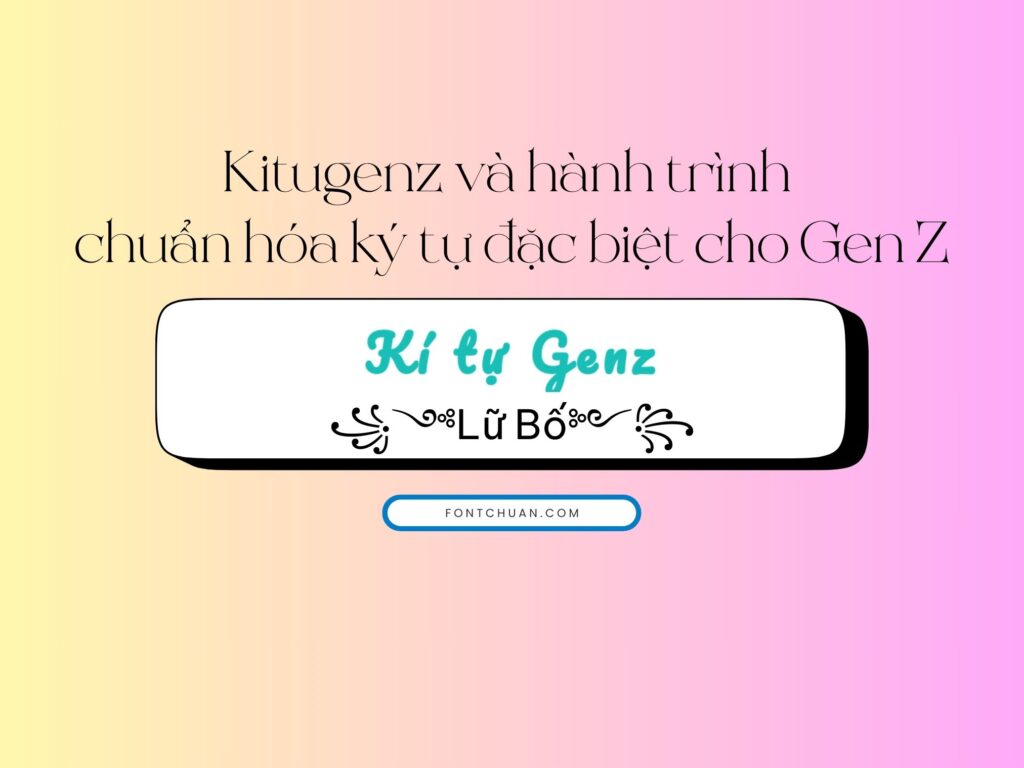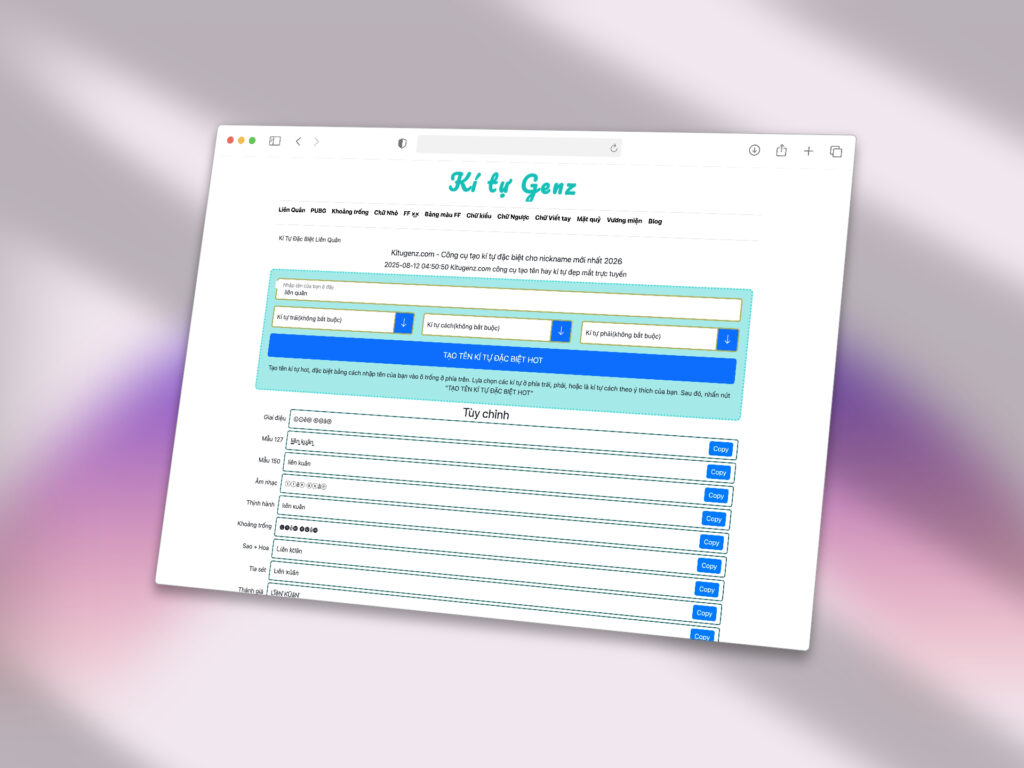
Kitugenz và hành trình chuẩn hóa ký tự đặc biệt cho Gen Z
Gen Z thích chữ kiểu. Tên game, bio TikTok, caption Instagram đều cần khác biệt nhưng vẫn dễ đọc. Kitugenz.com đáp ứng nhu cầu ấy bằng công cụ tạo ký tự đặc biệt và chữ kiểu. Khi người dùng tăng nhanh, một vấn đề xuất hiện: cùng một chuỗi ký tự nhưng hiển thị không đồng nhất giữa iOS, Android, web và các sảnh chờ trò chơi. Có nơi hiện ô vuông. Có nơi lệch dòng. Có nơi vỡ emoji. Kitugenz quyết định sử dụng dịch vụ chuẩn hóa ký tự của Font Chuẩn để xử lý tận gốc.
Bối cảnh và bài toán
Người dùng đến Kitugenz để đổi chữ rồi sao chép đi khắp nơi. Chuỗi tạo ra phải ổn định khi đổi nền tảng, đổi trình duyệt, đổi font. Thực tế có nhiều glyph trông giống nhau nhưng thuộc code point khác nhau. Một số nằm trong vùng Compatibility. Một số ở dạng Fullwidth. Một số lại phụ thuộc hệ thống fallback font của thiết bị. Khi thiếu chuẩn, nội dung có thể rụng dấu, dính khoảng trắng lạ, mất căn dòng. Trải nghiệm giảm. Khả năng tìm kiếm cũng bị ảnh hưởng khi bot đọc phải ký tự không tiêu chuẩn.
Mục tiêu
Mục tiêu đầu tiên là giữ chất Gen Z gồm ngầu, cute, tối giản, glitch nhưng vẫn đọc được ở mọi nơi. Mục tiêu tiếp theo là nâng tỉ lệ hiển thị đúng trên TikTok, Instagram, Facebook, YouTube, Discord và các trò chơi như Free Fire hay Liên Quân. Ngoài ra cần giảm lỗi sao chép dán và giảm thời gian tạo tên. Cuối cùng là giữ khả dụng cho máy tìm kiếm. Mỗi chuỗi nên có phiên bản Unicode thuần để lập chỉ mục ổn định.
Quy trình chuẩn hóa bốn pha
Pha một là kiểm thử và đo lường đa nền tảng. Font Chuẩn dựng ma trận thử nghiệm gồm iOS, Android, Windows và macOS. Trình duyệt gồm Chrome, Safari và Edge. Môi trường trong game cũng được đưa vào kịch bản. Hệ thống ghi nhật ký lỗi theo chuỗi và theo nền tảng. Các chuỗi được đối chiếu theo code point. Quy tắc phát hiện confusable giúp phân biệt chữ A Latin và А Cyrillic. Kết quả chỉ ra nhóm rủi ro tập trung ở NFKC Compatibility, Fullwidth Forms và một số ký tự tổ hợp.
Pha hai là xây dựng Bảng Ký Tự An Toàn Gen Z. Nhóm dự án lập danh sách ký tự an toàn theo nền tảng. Mỗi ký tự rủi ro có quy tắc thay thế tương ứng. Về chuẩn hóa, hệ thống lưu trữ theo Unicode NFC để thống nhất chuỗi. Khi xuất, hệ thống áp NFKC có kiểm soát để thu gọn biến thể mà vẫn giữ phong cách. Các chuỗi tổ hợp được giới hạn để tránh vỡ dòng. Với emoji, hệ thống định nghĩa fallback khi thiếu font emoji bản địa.
Pha ba là thiết kế hệ chữ và hướng dẫn sử dụng. Kitugenz có nhiều preset. Nhóm tái cấu trúc thành các bộ theo ý định tìm kiếm và ngữ cảnh dùng. Nhóm Cute dùng cho bio và caption. Nhóm Ngầu và Glitch dùng cho tên game và clan. Nhóm Minimal dành cho hồ sơ nghiêm túc. Mỗi preset có tên chuẩn SEO, mô tả ngắn, nhãn rủi ro hiển thị và gợi ý ghép với font Việt hóa. Đề xuất sử dụng OTF đậm cho tiêu đề và WOFF2 gọn nhẹ cho nội dung dài. Hướng dẫn quy định kerning, tracking và line height để chống đứt dòng. Cấu hình fallback font theo từng hệ điều hành giúp giảm lệch kiểu.
Pha bốn là triển khai kỹ thuật và trải nghiệm. Hai chức năng then chốt gồm bộ lọc ký tự và sao chép thông minh. Bộ lọc so chuỗi với danh sách an toàn. Nếu gặp rủi ro, hệ thống gợi ý thay thế tức thì và ghi lý do ngắn gọn. Sao chép thông minh cung cấp hai nút. Nút Giữ phong cách sao chép đúng kiểu chữ. Nút Plain Unicode tạo bản sạch để dùng cho SEO và những nơi chặn ký tự. Giao diện có xem trước theo nền tảng. Nhãn rủi ro hiển thị được đặt gần nút sao chép. Microcopy giải thích rõ: chuỗi này có thể không hiển thị trong một số trò chơi cũ. Phần nội dung chữ kiểu được cache và phân phối qua CDN để giảm độ trễ.
Quy trình chuẩn hóa bốn pha kitugenz
Kết quả và tác động
Sau khi chuẩn hóa, trải nghiệm hiển thị trở nên đồng nhất hơn. Người dùng truy cập kitugenz.com/ki-tu-dac-biet-lien-quan ít gặp ô vuông, đứt dòng và lỗi dán. Thời gian hoàn tất tên game giảm đáng kể. Tỷ lệ chia sẻ preset tăng vì người dùng tự tin rằng chữ sẽ hiển thị đúng ở nơi khác. Hình ảnh thương hiệu tốt hơn. Các màn hình chính giữ nhịp điệu thị giác ổn định về cỡ chữ, khoảng cách và độ đậm. Chuỗi văn bản trông mạch lạc dù người dùng đổi nhiều preset khác nhau.
Hiệu quả tìm kiếm cũng cải thiện. Mỗi trang preset có mô tả ngữ nghĩa rõ ràng. Từ khóa liên quan gồm chữ kiểu Gen Z, ký tự đặc biệt, đổi tên game và Unicode an toàn. Dữ liệu có cấu trúc phù hợp giúp máy hiểu nội dung. Phiên bản plain text dành cho bot hạn chế rủi ro đồng bộ. Điều này giúp công cụ tìm kiếm lập chỉ mục ổn định và tăng cơ hội hiển thị trích đoạn đẹp.
Bài học rút ra
Bài học đầu tiên là đẹp phải đi cùng chạy được. Unicode không chỉ là bảng mã mà còn là thỏa thuận giữa sản phẩm và hệ sinh thái. Tôn trọng NFC và NFKC giúp chuỗi bền vững khi truyền qua nhiều lớp. Bài học thứ hai là xem fallback font như dây an toàn. Cần định nghĩa stack rõ ràng và thử nghiệm theo kịch bản. Bài học thứ ba là không lạm dụng glyph hiếm ở vị trí trọng yếu như tiêu đề dài và khẩu hiệu. Hãy coi chúng là gia vị. Bài học thứ tư là quản trị bằng dữ liệu. Ghi lỗi theo code point, cập nhật danh sách an toàn theo quý và công bố thay đổi để cộng đồng nắm được. Bài học cuối là đặt tên preset theo ngữ nghĩa và mục đích. Tên rõ ràng giúp người dùng tìm đúng, máy hiểu đúng và mô hình ngôn ngữ trích xuất thực thể chính xác.
Hành trình cùng Kitugenz chứng minh rằng chuẩn hóa ký tự đặc biệt không làm giảm cá tính. Chuẩn hóa giúp cá tính xuất hiện đúng chỗ và đúng cách trên mọi nền tảng. Khi tầng kỹ thuật vững gồm Unicode, chuẩn hóa chuỗi, sanitizer, fallback và định dạng WOFF2, OTF, TTF, tầng trải nghiệm sẽ cải thiện rõ rệt. Người dùng gõ, nhìn, sao chép và dán. Thông điệp vẫn nhất quán. Đó là tiêu chuẩn cho sản phẩm chữ kiểu phục vụ Gen Z hôm nay. Táo bạo về phong cách. Kỷ luật về kỹ thuật. Mạch lạc về ngôn ngữ.